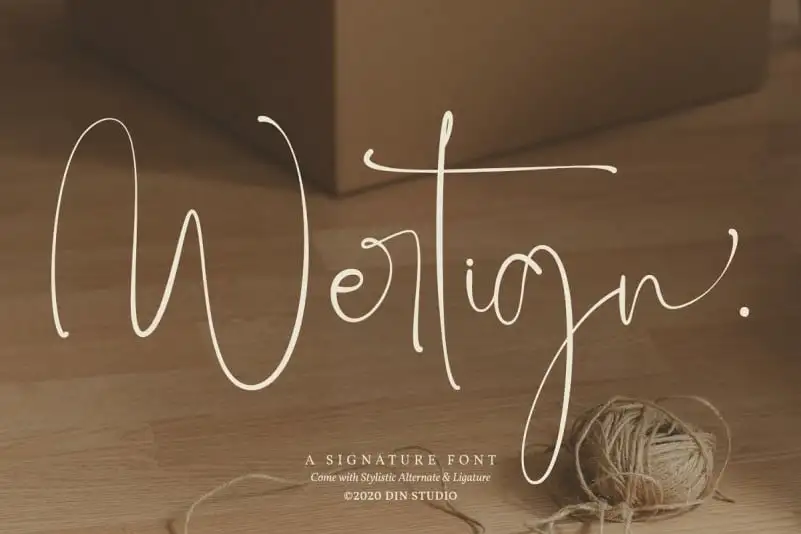
Wertign Script Font – Download Grátis
A ‘Wertign Script Font’ é uma fonte script com aparência elegante e minimalista que oferece ligaturas e caracter especiais para tornar seu design ainda mais sofisticado. Suas ligações finas, combinadas a um estilo elegantemente minimalista, tornam essa fonte versátil o suficiente para trabalhar tanto em tamanhos grandes quanto pequenos. Ela é perfeitamente adequada para uso em websites, marcas sociais, banners da Pinterest e produtos impressos. A ‘Wertign Script Font’ captura a essência da estética moderna, ao mesmo tempo que oferece um toque nostálgico. Ela se destaca em qualquer projeto, seja ele para uma publicidade ou promoção. É perfeita para quem busca um desafio criativo e busca dar vida aos seus projetos digitais e impressos de maneira única.